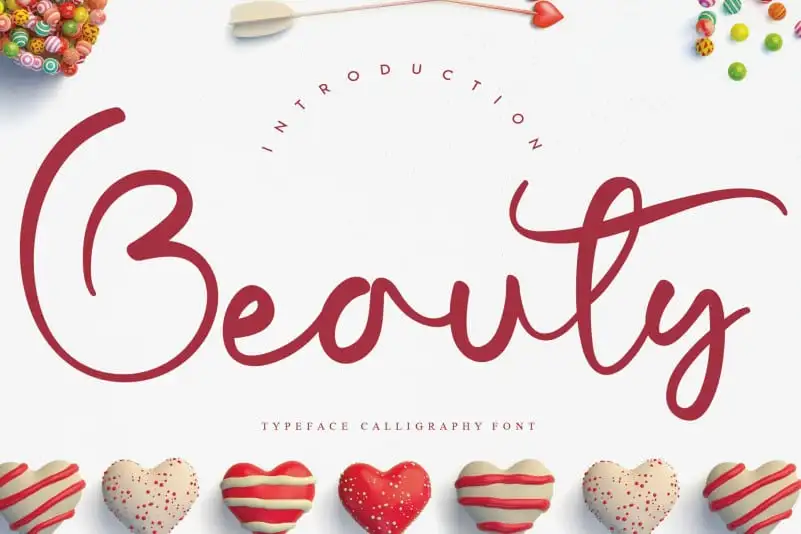
Beauty Script Font – Download Grátis
A ‘Beauty Script Font’ é uma elegante escolha para designers que valorizam beleza e simplicidade na tipografia. Desenvolvida pelo designer creativletter, esta fonte script oferece um toque delicado e sofisticado às suas criações digitais. Com linhas finas e curvas arredondadas, a ‘Beauty Script Font’ é perfeita para textos de design gráfico que buscam expressar uma personalidade única e envolvente. Suas caligrafias fluidas permitem aos designers criar mensagens sutis e românticas sem comprometer o impacto visual do projeto. Seja em criações de branding, editoriais ou até mesmo para adicionar um toque artesanal a qualquer tipo de conteúdo digital, esta fonte oferece uma maneira linda de expressar sua personalidade criativa. O design é ideal tanto para designers que buscam algo romântico e delicado quanto para aqueles que desejam criar algo mais sofisticado e elegante. Com ‘Beauty Script Font’, você pode estilizar seus projetos com um toque único, tornando cada texto uma verdadeira obra de arte digitais.